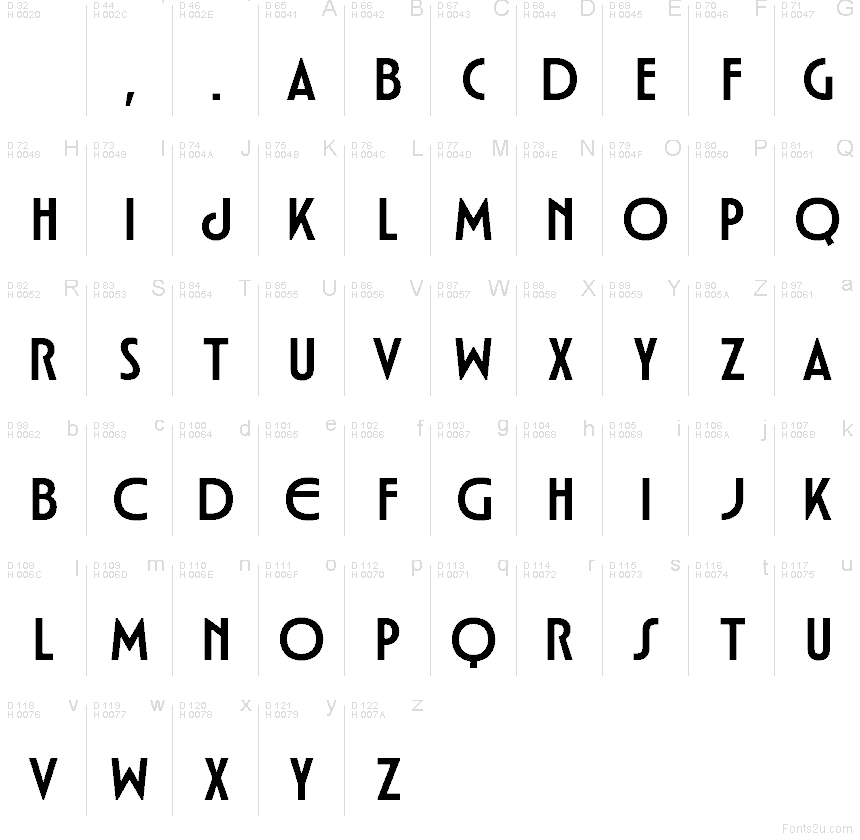
Il font Crostan Semi Bold di Bagus Arya Kirana (Genetype) conferisce alla famiglia Crostan un’atmosfera Art Déco dal tocco sci-fi: forme slanciate e pulite, curve sinuose e tratti decisi e sicuri. L'effetto è elegante e architettonico, con un ritmo serrato che mantiene una chiarezza visiva impeccabile anche nei formati grandi. Crostan Semi Bold è un font sans serif moderno e gratuito, capace di catturare l'attenzione immediatamente da qualsiasi distanza.
Con Crostan Semi Bold otterrai risultati di grande impatto per branding tecnologico, splash screen di app, grafica per esports, locandine cinematografiche, copertine di album, lookbook di moda e insegne di negozi. È perfetta anche per titoli brevi su packaging e inserzioni social, dove serve un mix di chiarezza e personalità. Abbina questo font gratuito a una grottesca neutra o a una sans umanistica per il testo principale, aumentando leggermente il tracking per far respirare meglio i caratteri.